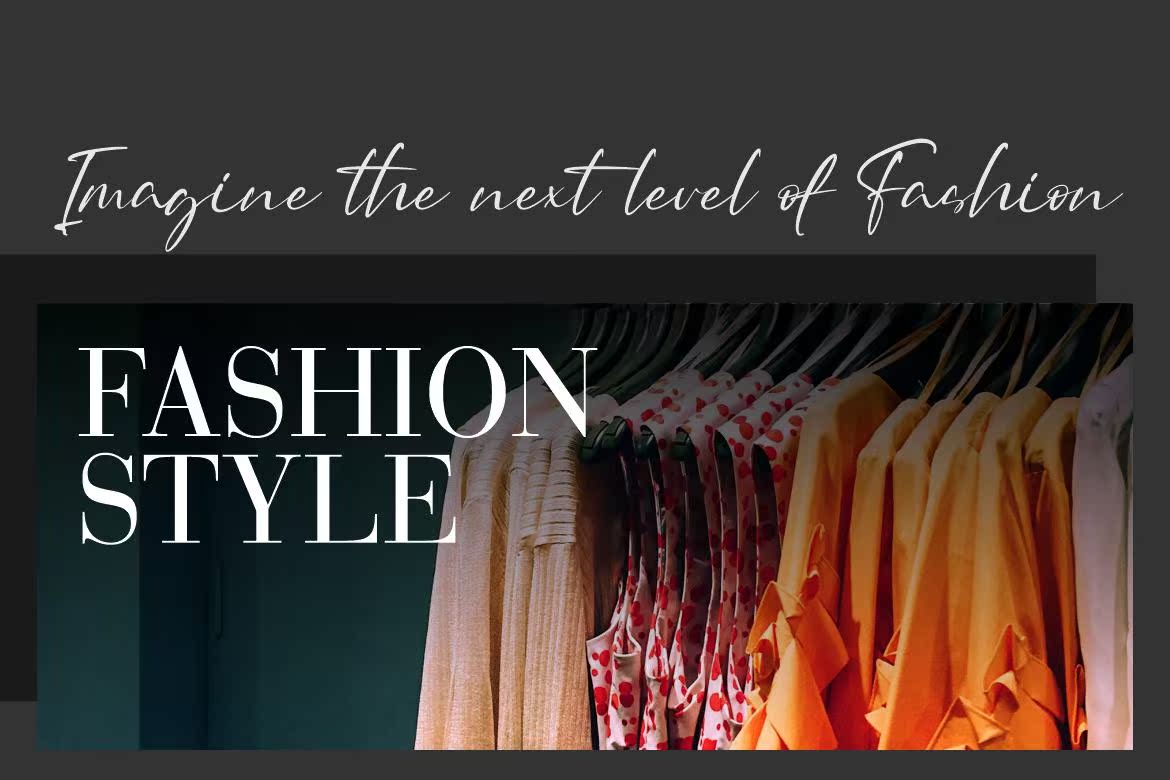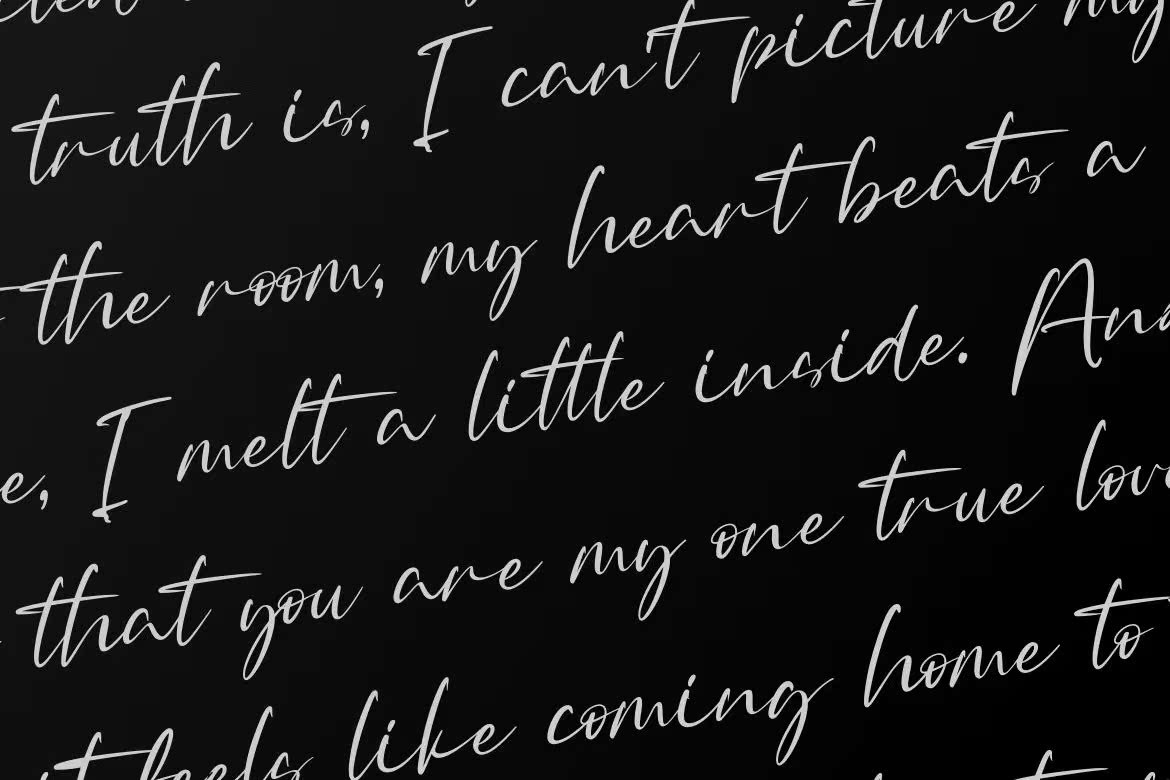
Rotenfoldisbeautiful,elegant and natural and writent字体。此字体是创建徽标、水印、品牌、婚礼宣传、报价或任何内容的完美选择。让我们用此字体制作一些美丽的项目。Rotenfoldisbeautiful,elegant and natural and writent字体。此字体是创建徽标、水印、品牌宣传、婚礼宣传、报价的完美选择,或者任何东西。让我们用这个做一些美丽的项目。